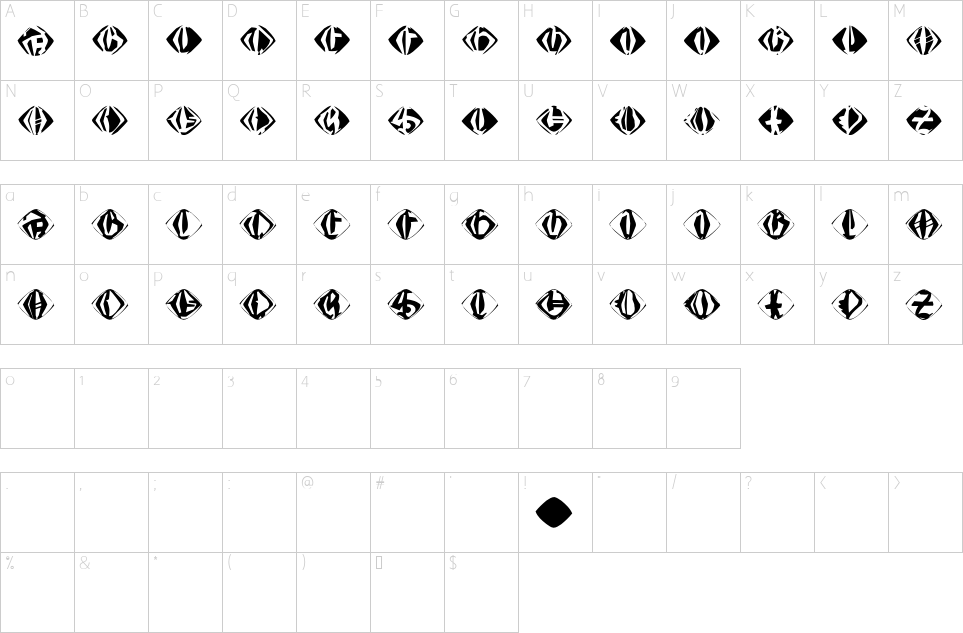
JohGDiamonds é uma fonte elegante e sofisticada, perfeitamente adaptada para design gráfico e criação de materiais digitais. Criada pelo artesão Manfred Klein, essa fonte única oferece um visual moderno e moderno que se adapta a diversos estilos de design. Seja você um designer de moda, um criador de conteúdo de redes sociais ou um artista gráfico, JohGDiamonds é uma escolha inteligente para personalizar seus projetos digitais. Com 1,168 downloads, é claro que muitos usuários já aprovaram suas capacidades únicas e sua estética deslumbrante. Download JohGDiamonds para Windows e Mac hoje e experimente a versão gratuita de alta qualidade, sem comprometer o design.